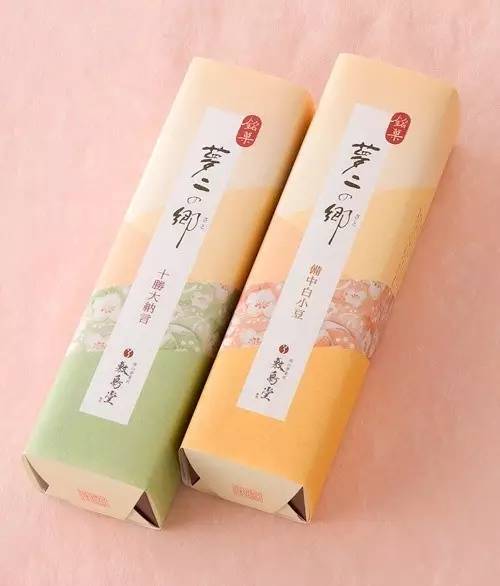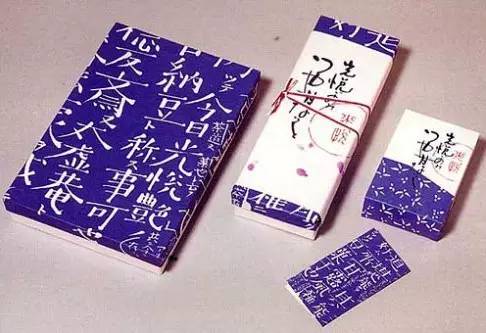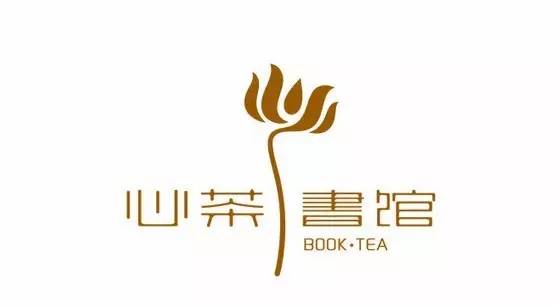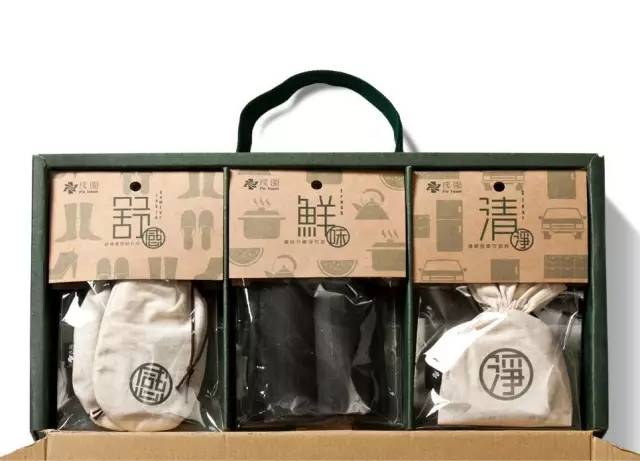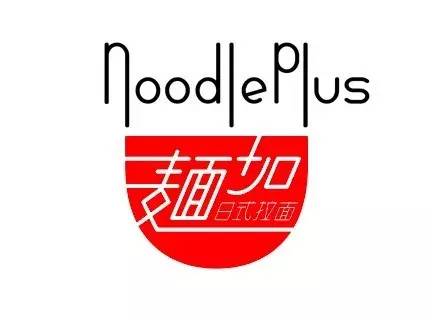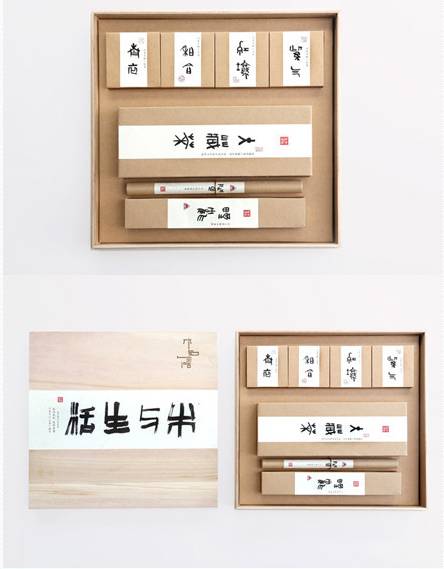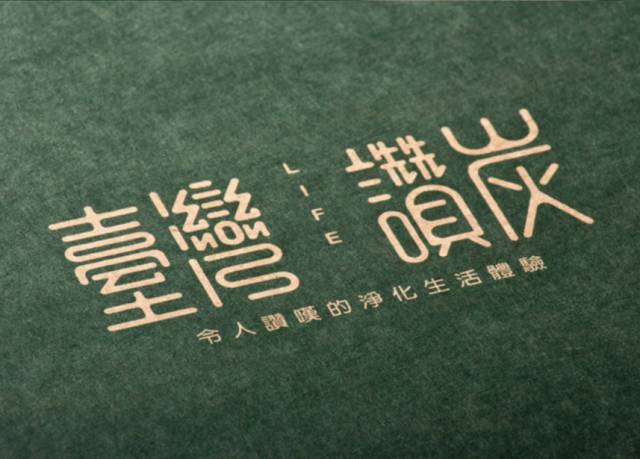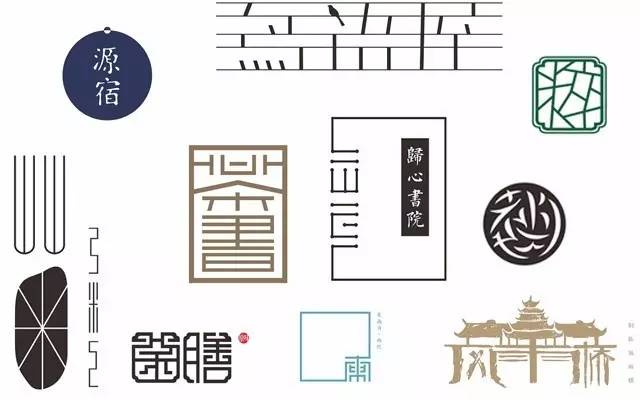
都喜欢用英文做设计,汉字到底怎么了?
难道是“国外的月亮比较圆”,所以我们本能地抗拒产品设计中出现汉字吗?很多人对国外品牌趋之若鹜,客户和设计师们都小心翼翼,生怕一不小心用错汉字失去用户的心。
我们或许都曾有过这样的经历,看到一些产品设计上印有中文字样,会突然失去购买欲望。甚至连一些大牌都逃不过这样的心理落差,比如LV或Louis Vuitton看起来很高级,一旦广告上打出“路易威登”,简直自带乡土气息的光芒。前段时间,airbnb官方认证中文品牌名称为“爱彼迎”,有多少人哭着表示再也不在爱彼迎上定住宿了?
难道是“国外的月亮比较圆”,所以我们本能地抗拒产品设计中出现汉字吗?很多人对国外品牌趋之若鹜,客户和设计师们都小心翼翼,生怕一不小心用错汉字失去用户的心。但这不是设计中拒绝汉字的主要原因。到底是什么造成这样的主观认知?设计中汉字真的是一个不能踩的雷区吗?
汉字会带来廉价感吗
越是熟悉的文字越容易带来廉价感。我们试着回想一下,当看到印有汉字的产品,不论是包装、T恤还是品牌标志…第一时间会去解读字面意义,“这是什么?” “写的是什么意思?” 并不断引申出进一步含义。
比如在T恤上印着“绿”字,第一眼看到的不是字体设计、字形排版、图案搭配…而是大写的“绿”。在我们看来,这不是设计图形或符号,而是再熟悉不过的文字。正是这种与生俱来的习惯认知,造成我们过度解读汉字后产生的廉价感。
在习惯英文的国外地区,他们对于英文的直接使用和简单解读也有着本能抗拒。很多欧美品牌在Logo设计和产品设计时,会更倾向于选择大写字母或自创单词组合,比如GUCCI、COACH、NIKE、CHANEL…虽然英文作为主体,但这是独创的字母组合,无法一眼解读字母含义,而避免了熟悉所造成的廉价感。
正是这样的文化心理偏差,我们会发现,很多外国人特别热爱汉字设计。在他们看来,汉字是多么美妙的存在,丰富的字体表达、古老东方的神秘文化,不会去刻意理解汉字的意思,而是作为图形或符号化表达。甚至,很多在我们看来很奇怪的汉字,外国人会乐此不疲地穿在身上,纹中文纹身,比如“蠢”、“怂”他们看来有种别样的对称美。
距离产生美。在设计中,设计师需要做到如何不让设计第一眼就被解读出来。人的大脑拥有复杂而神奇的构造,当对某一事物的认知反应越慢,会觉得设计越好看。这样看来,汉字真的无用武之地了吗?汉字设计只能与廉价感挂钩吗?当然不是,东方气韵、汉唐风骨,又岂能一语以概之。
难道汉字不能设计好吗
当我们了解到多么难扭转对汉字的熟悉认知,创造出优美简洁的汉字设计时,可能一些设计师会选择放弃,转而不断使用更简单、更普遍的英文甚至其他外文,让用户轻易产生图形符号认知。然而这也束缚了设计更多的可能性。
我们在局限于汉字的功能含义时,却忘记汉字本身就是美的存在。汉字之美,美誉天下,积淀华夏文化五千年的古老传承,从象形符号到篆、隶、楷、行草诸体,从用笔、结构、造型等的不断演化,构成汉字的写意形式美。字体的气韵生动、千变万化,更是难得的书写艺术。然而在设计中,我们却甚少愿意使用汉字,这会不会太过可惜?
越是难以设计好看的元素,通过好的设计越是能发挥出不可思议的魅力。汉字正是这样的存在,更考验设计师的专业能力和孜孜以求的设计精神。
从美感上而言,繁体字是比简体字更美好的存在。简体字的出现是为了文化普及的需要,正是因为简体字太过熟悉,在设计中使用繁体,从其字形字意字体上设计变化,更具灵感和发挥创造性的空间~
而相较于英文,汉字本身的构造就已非常复杂。一个英文单词可能并无意义,但是一个繁体字就可以表达出丰富的含义,对排版设计要求更高。如何让复杂的繁体字充分融合于设计中?不如让背景画面越简单越好,突出汉字设计感~
从我们的视觉感知上,如果所有元素都繁复地堆砌在一起,找不到重点,更难以体会繁体字的独特美感。
段落、留白、字体、间距、意境…每一个微小细节的调整都会让汉字表达更富感情、彰显个性~就如我们普遍认知的“Less is more”是一种设计规范,但不是唯一的设计准则。在汉字设计中,我们遵循这些设计方法,却也不局限于此,更多跳跃的、律动的设计尝试,也许会重现不一样的汉字风采。
钟灵毓秀,天地人杰,孕育千百年的汉字形体,在我们看来本身就是美的存在。
如何设计可以打破字体局限性
当我们比较字体、图形符号设计时,确实发现字体存在的局限性。很多时候,用户在记忆一个品牌时,图形会更具辨识度。文字有跨越国家之间的文化障碍,但图形不会,甚至能表达出更多层次的意义。比如我们所熟知的“STARBUCKS”依然设计了标志性的双尾美人鱼Logo,比如享誉世界的法国葡萄酒品牌拉菲,可能一开始不能立刻想起法语“Lafite”,却能想起品牌标识中的五只箭头…
在产品的外观设计中,将图形和汉字结合会是一种不错的尝试。汉字往往给人严肃、刻板、方正的感觉,如果觉得只有汉字太过单调乏味,融入一些具有东方元素的图形风格,增加意境。比如油纸伞、纸扇、桃花、牡丹、水墨、绸缎、旗袍…这些独有的意象元素适当地融入到汉字设计中,而不喧宾夺主,将产生令人心动的美好,这是设计的力量。
在这一点上,台湾香港、甚至日本都极具代表性,他们真正理解了东方审美的精髓,并运用在设计中。
我们知道,中英文结合往往会有一些违和,就像有人说话时中文夹杂着英文让人产生不适感。但在汉字设计中,越来越多的设计师开始尝试融入一些英文做装饰,可以填补不必要的空白,使整体设计更加的立体丰富。
将极难展现的汉字设计巧妙地运用字体字形、大小排版、图形配色等所有元素的融合,这才是设计的价值。我们不会说:“oh不,这太难了,无法设计。” 而是开始换一种思维,如何通过设计解决问题,当我们越来越重视汉字在产品设计中的运用,汉字或许会成为设计界的一种新趋势~